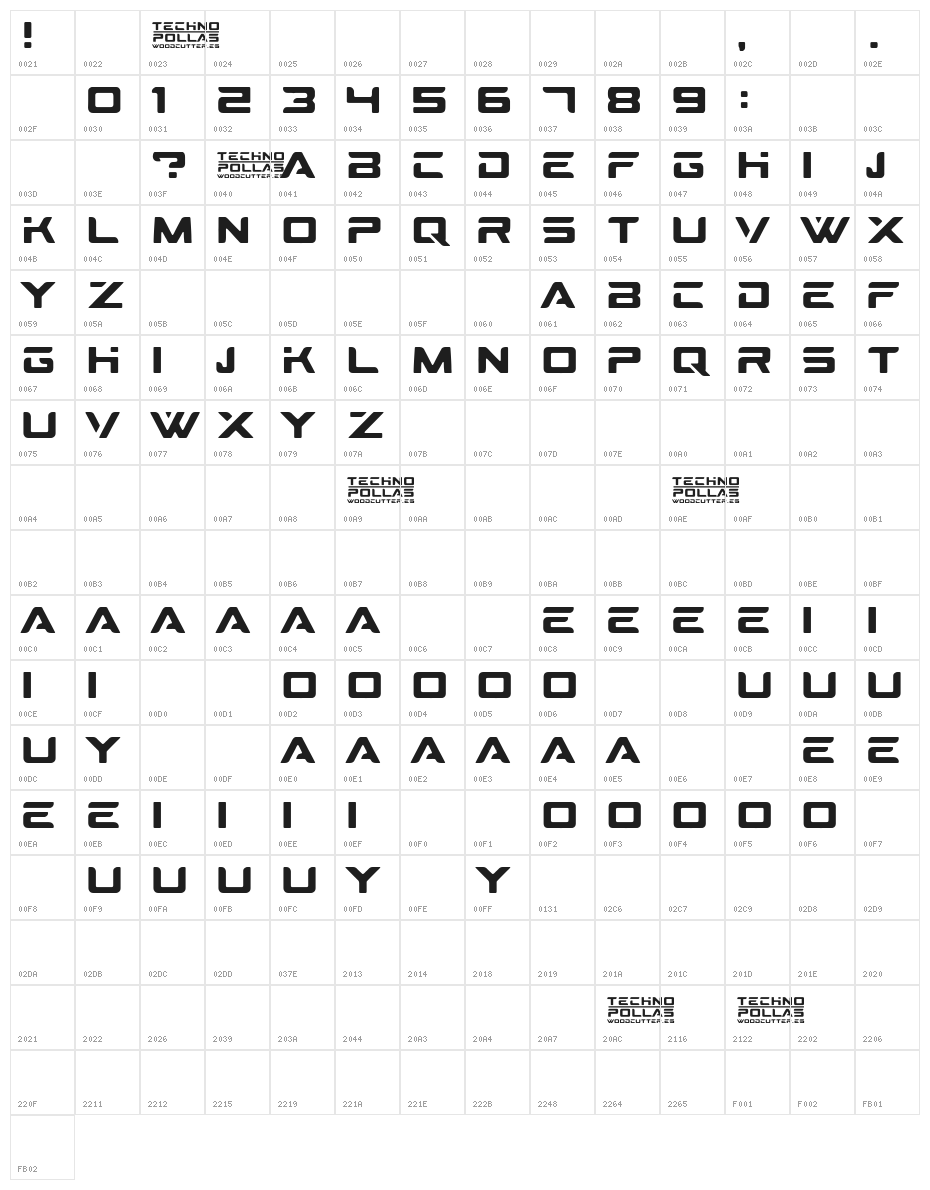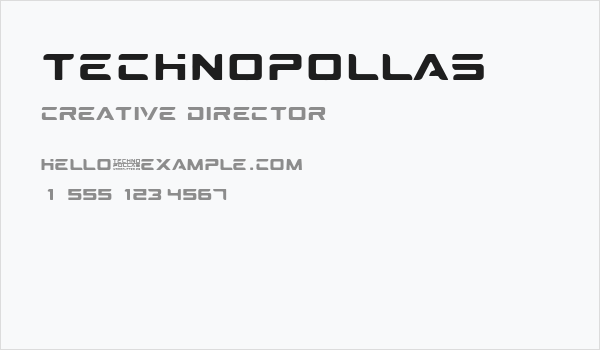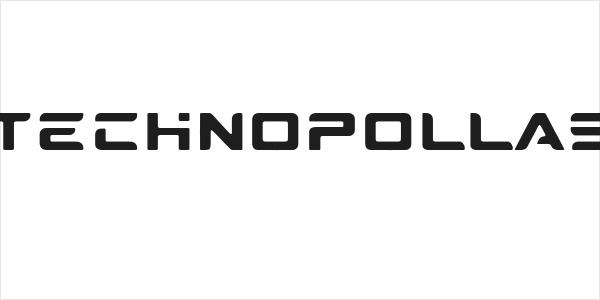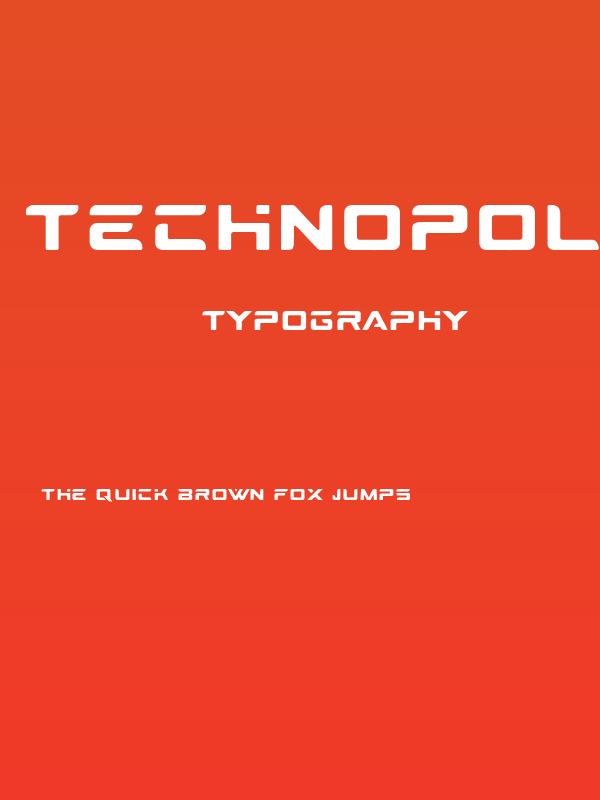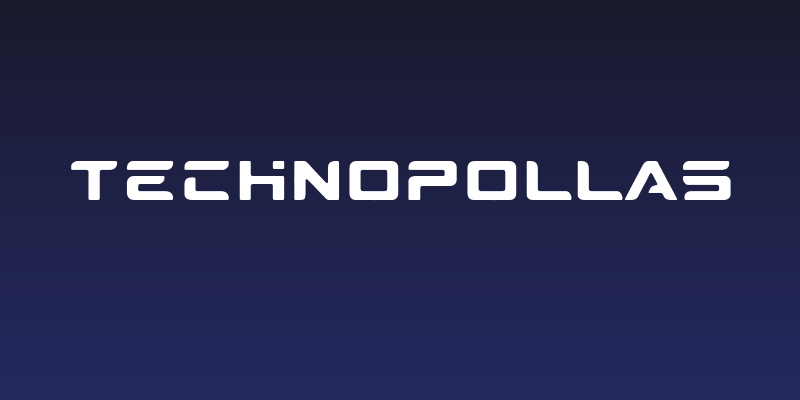
Technopollas Font
| 用途 | Logos, Headlines, Digital Interfaces |
| おすすめプロジェクト | Ideal for technology branding, sci-fi themes, digital interfaces, and modern advertising. |